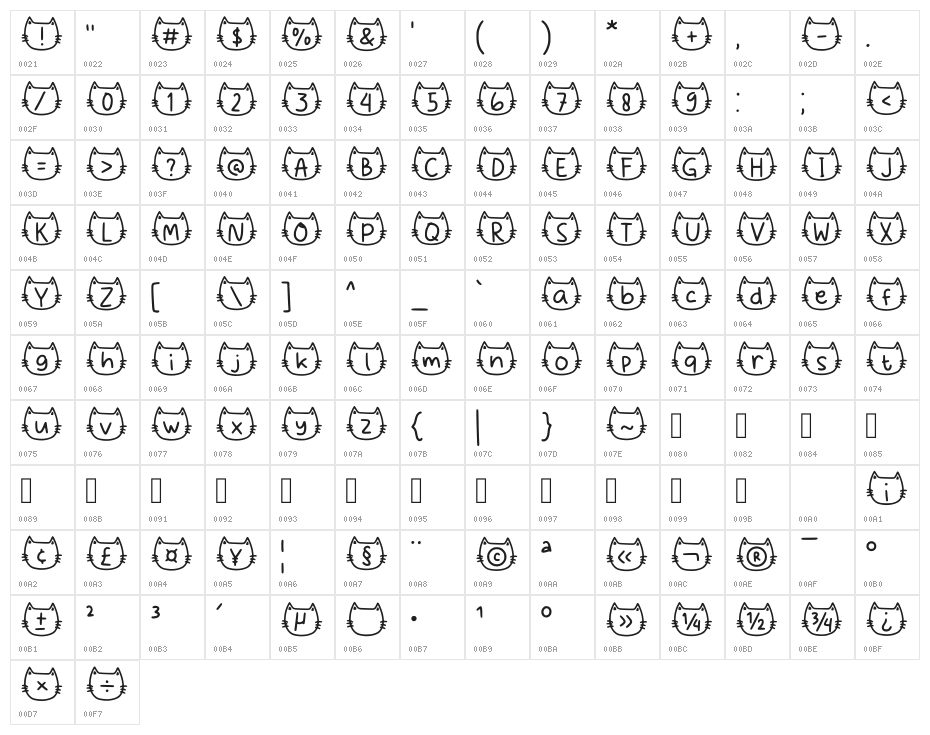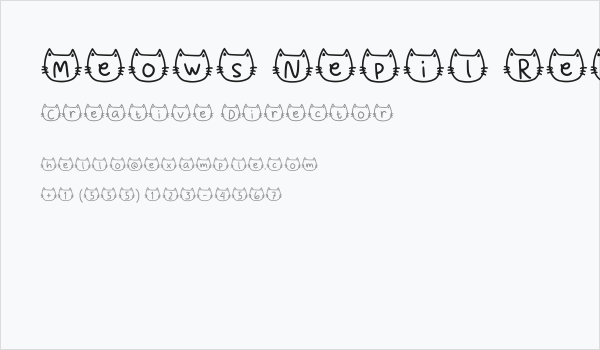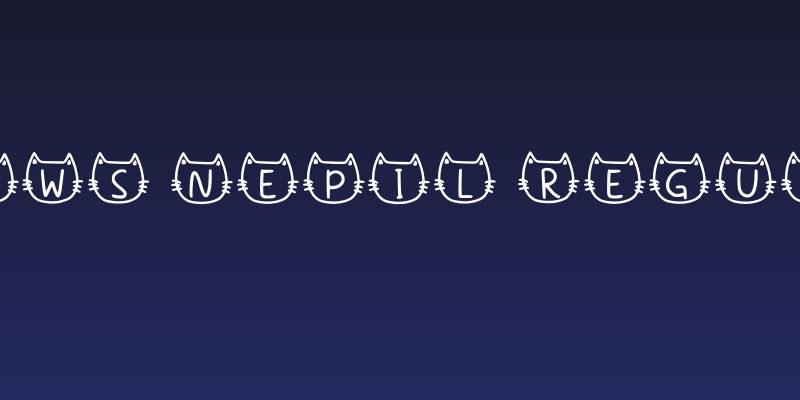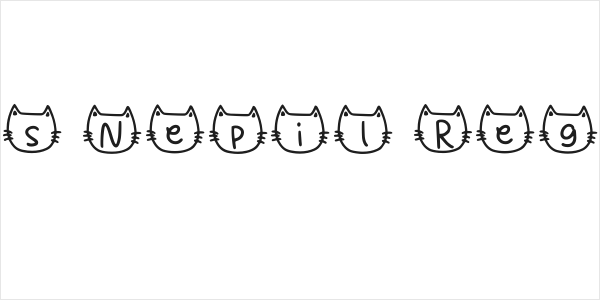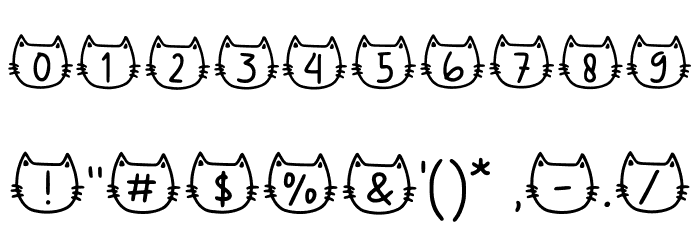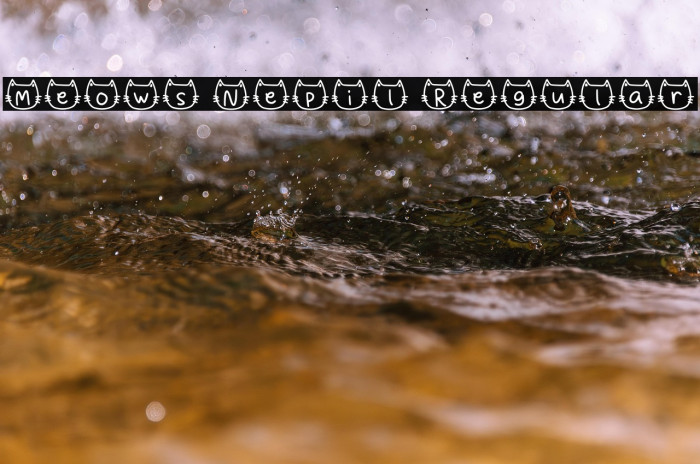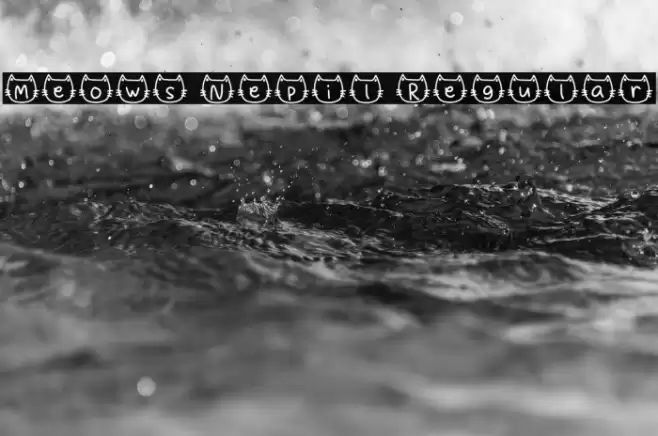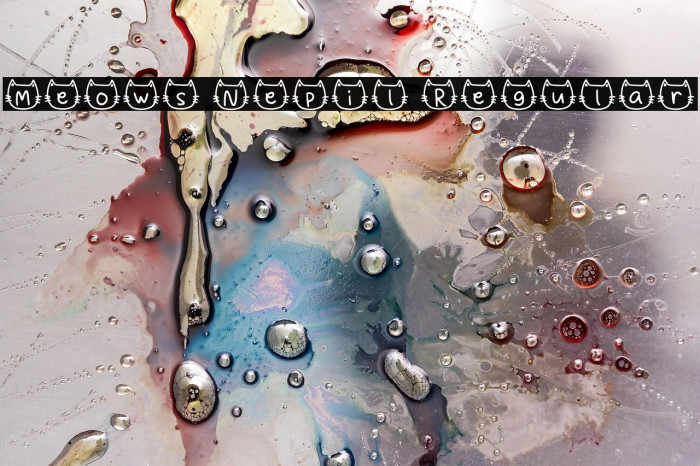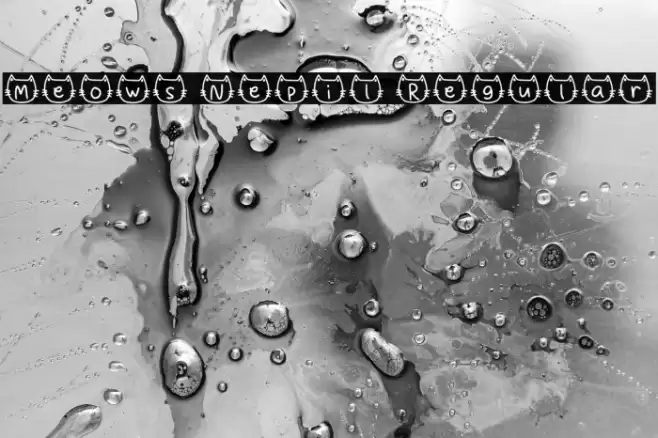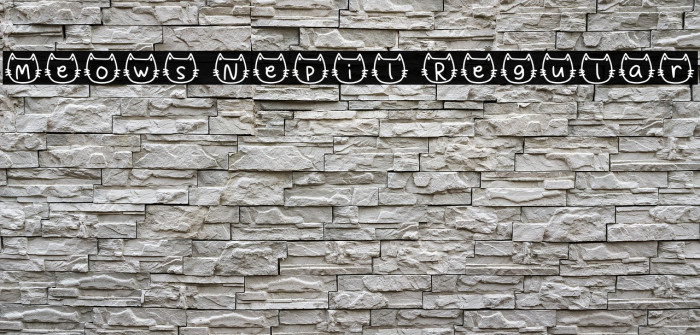
Meows Nepil Regular Font
| النمط العام | Whimsical, Playful, Decorative |
| حالة الاستخدام | Headlines, Logos, Decorative text |
| مشاريع مقترحة | Children's books, pet-related branding, playful event invitations, greeting cards, and novelty merchandise. |